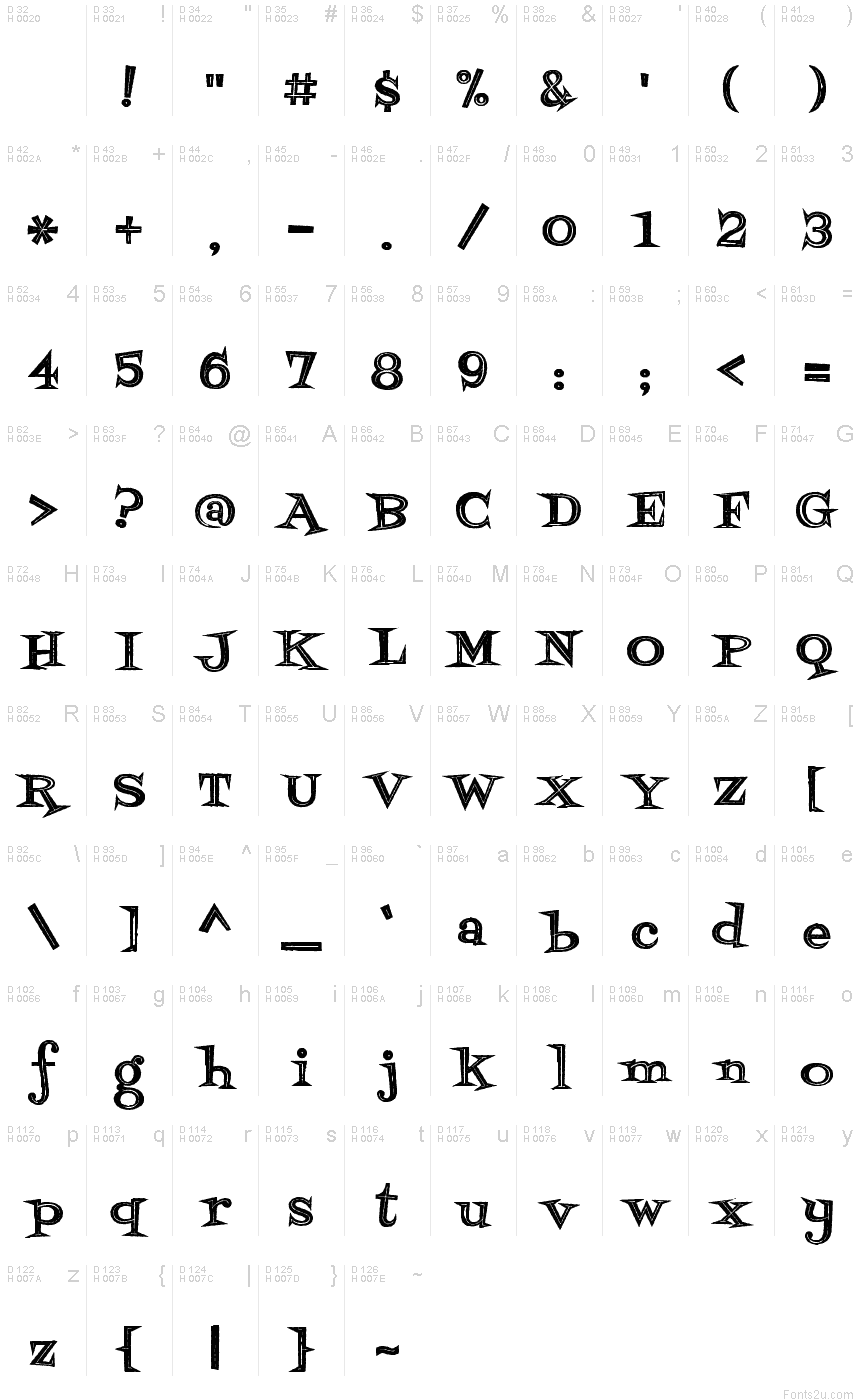
Fontdinerdotcom Jazz Dark od Font Diner je bezplatné, ručně kreslené display písmo s uvolněnou atmosférou vintage klubu. Písmena kombinují drátkovité patkové tvary s hrubými, skicovitými obrysy, takže celé písmo působí lehce improvizovaně, jako nápis na zašlém plakátu nebo starém obalu desky.
Přirozeně zapadne do hudebních letáků, retro obalů, titulků v časopisech, úvodních karet i vizuálu barů nebo kaváren, kde má bezplatné písmo navodit onen osobitý noční nádech. Použijte ho zejména pro krátké nadpisy a loga, protože nepravidelné tahy a lehce rozevlátý rytmus dodávají i jednoduchým slovům živý, „swingující“ charakter.